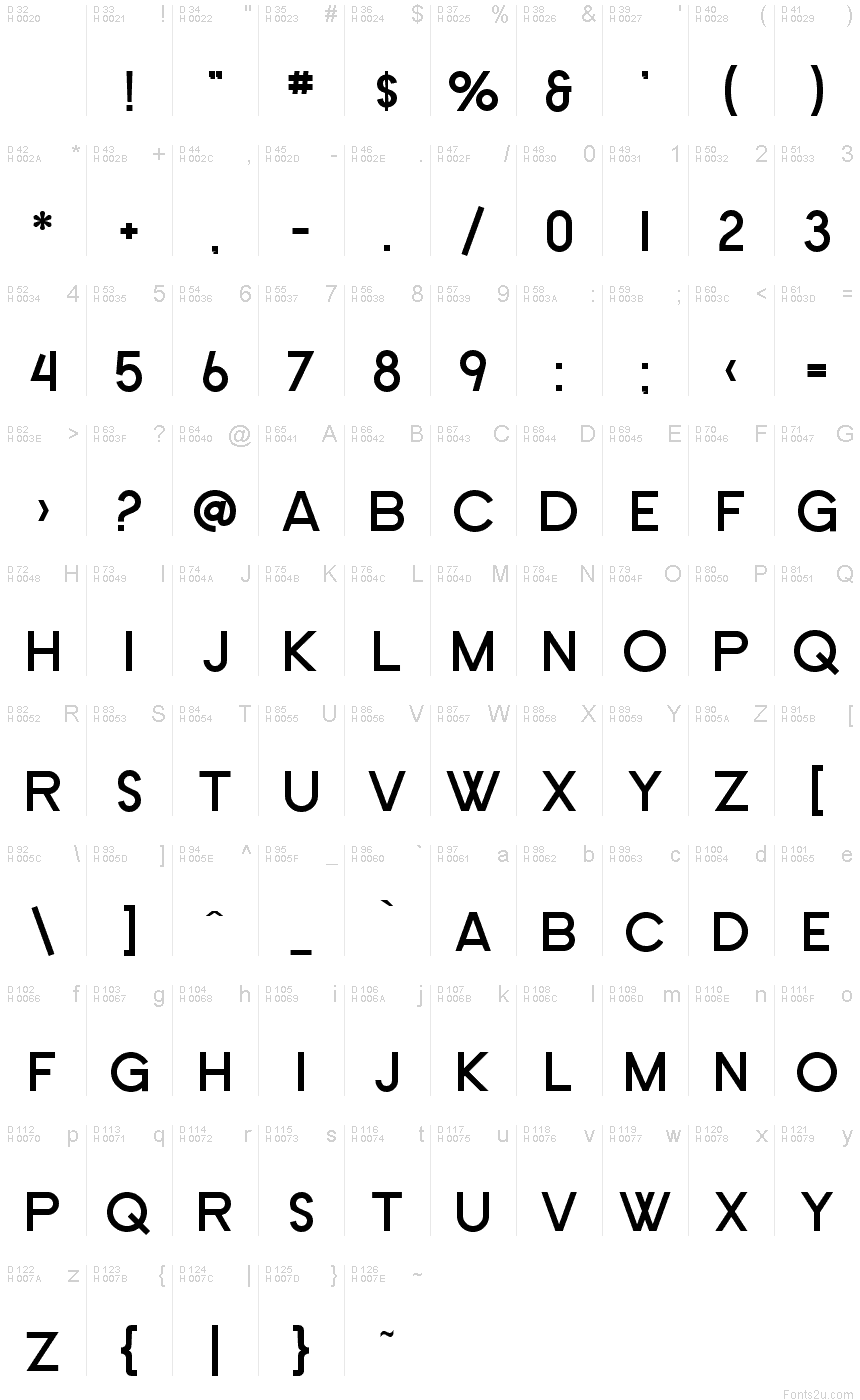
SF Old Republic SC Bold od ShyFoundry to bezpłatny, geometryczny krój pisma w klimacie science-fiction, przypominający swoją stylistyką plakaty z epoki Republiki. Litery wydają się jednocześnie ascetyczne i podniosłe – szerokie, koliste formy, proste łączenia oraz świadoma równowaga między wolną przestrzenią a wyrazistym ciężarem nadają wielkim literom eleganckiego, futurystycznego charakteru.
Świetnie sprawdzi się w brandingu gier i wydarzeń technologicznych, przy tytułach filmowych, nagłówkach plakatów, okładkach i monogramach, gdzie krótkie słowo wymaga wyraźnego akcentu science-fiction. Jako darmowy font najlepiej prezentuje się w krótkich napisach, ponieważ okrągłe O oraz kanciaste L i D tworzą wyrazisty rytm, idealny do nazw, emblematów i znaków frakcji.
SF Old Republic SC
ShyFoundry
Derek Vogelpohl